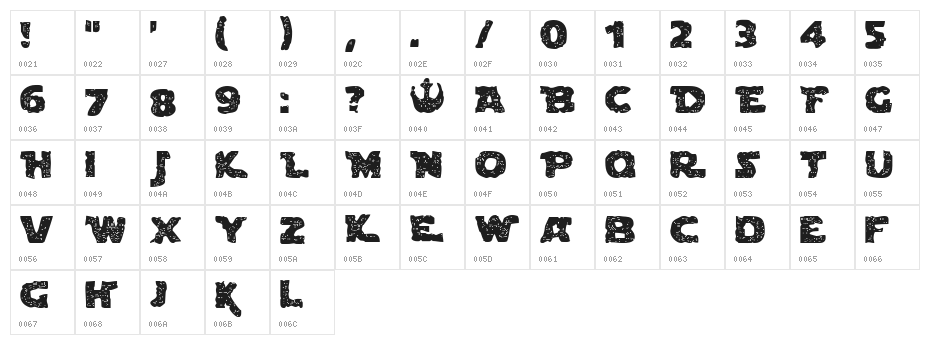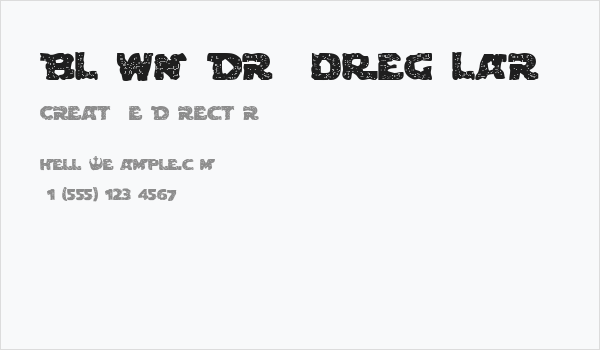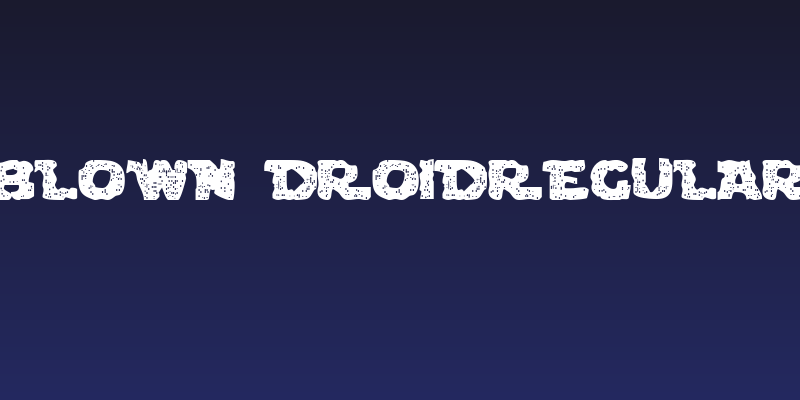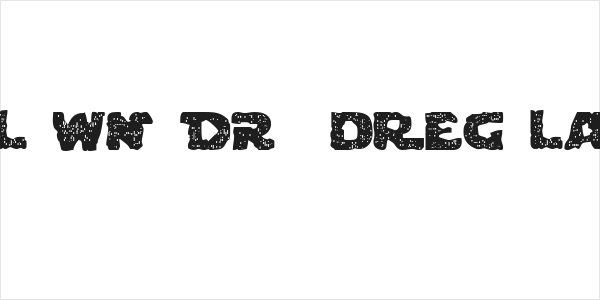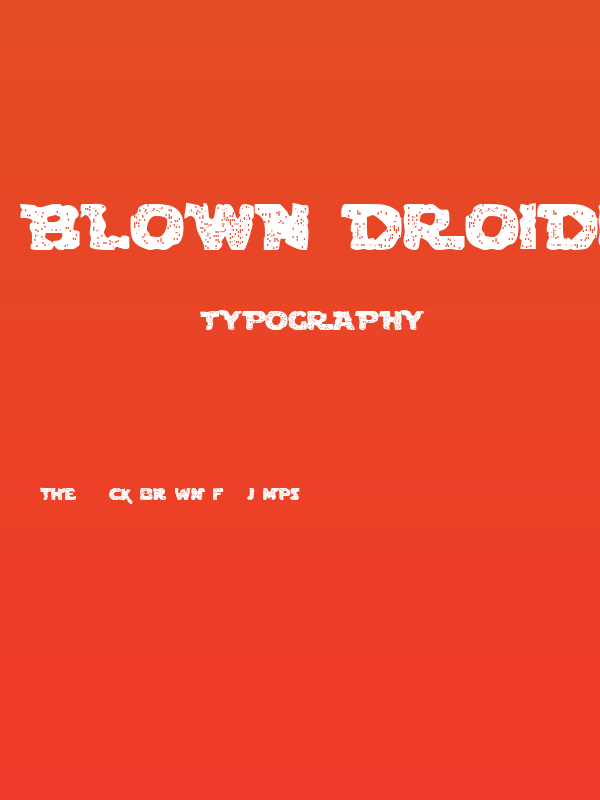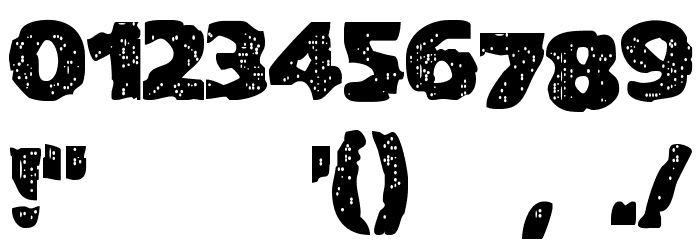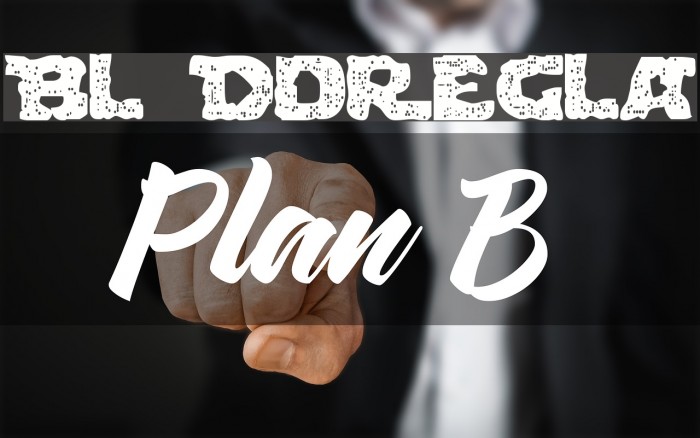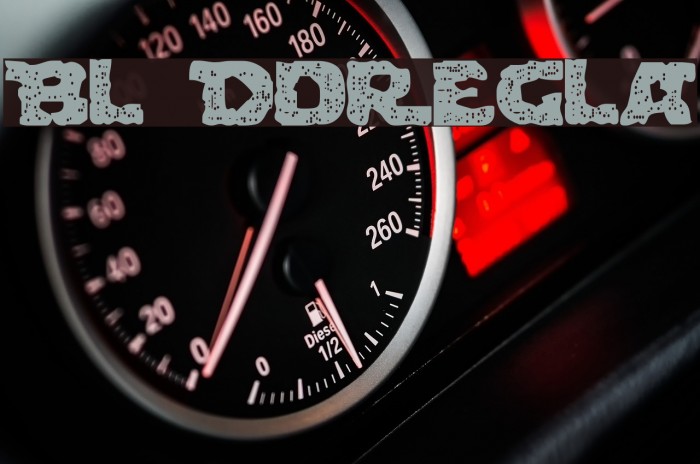
Blown DroidRegular Font
✎ Crazy
| Gesamtstil | Vintage |
| Vorgeschlagene Projekte | Perfect for posters, album covers, branding for rustic or vintage-themed products, and artistic projects. |